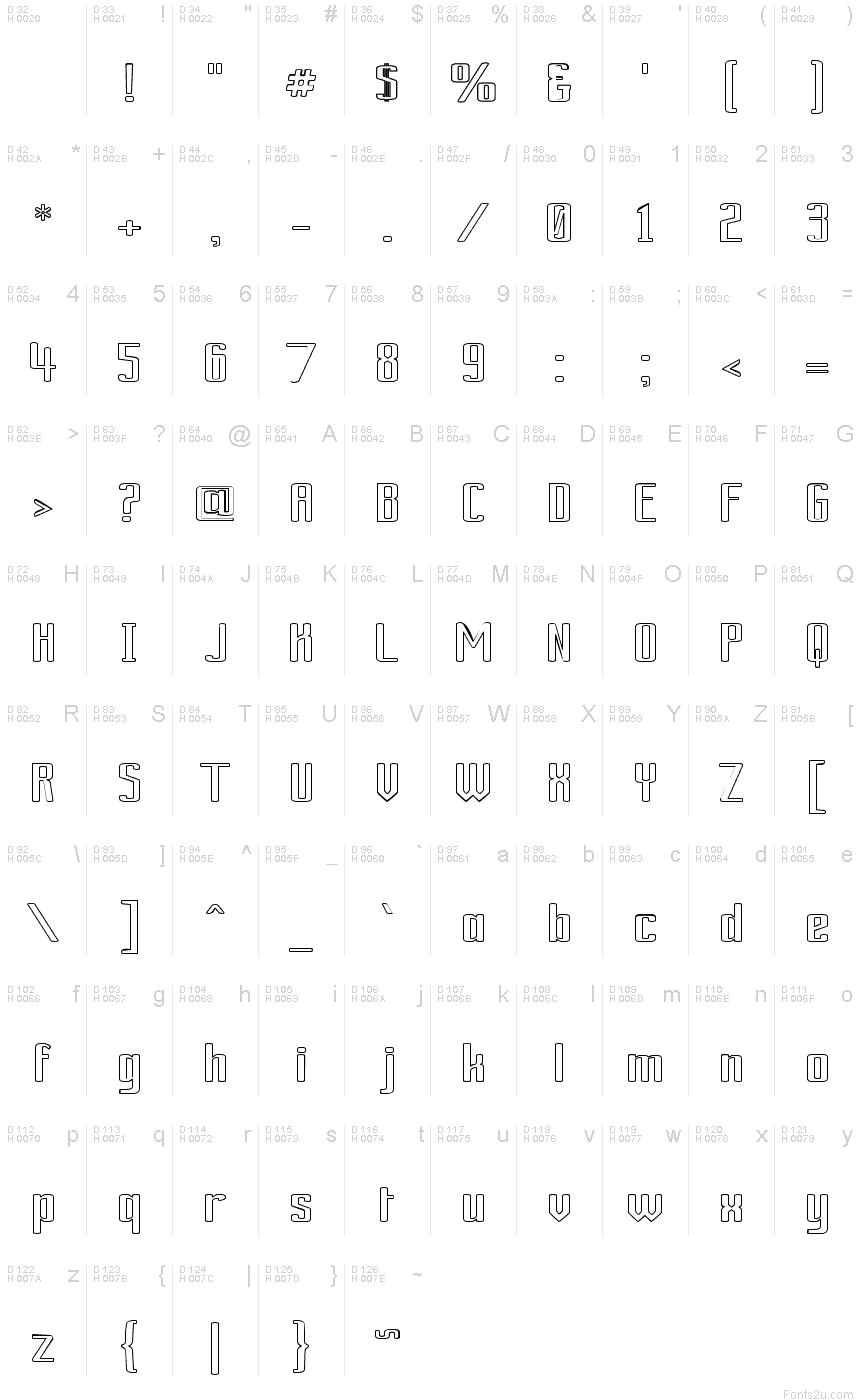
خط Ardour Outline من تصميم Graham Meade هو خط عرض مجاني مفرغ يتميز بطاقة ناعمة وأنبوبية تجعله يبدو وكأنه مرسوم يدوياً بأسلوب تزيين القوالب. تمنح مستطيلاته الدائرية وخطوطه المنتظمة الحروف مظهراً حيوياً ومنتفخاً، بينما تحافظ هندسته النظيفة على حدته وسهولة قراءته. تدعو المساحات المفتوحة داخل الحروف إلى دمج الألوان أو الأنسجة أو الصور، مما يحول كل كلمة إلى إطار يمكنك التصميم بداخله.
مع خط Ardour Outline، تكتسب العناوين والشعارات فوراً لمسة مرحة ذات طابع مستقبلي كلاسيكي (ريترو)، مع الحفاظ على مظهر نظيف ومعاصر. يتألق هذا الخط المجاني في الملصقات، وأغلفة الألبومات، وعناوين الألعاب، وعلامات الأطفال التجارية، والتغليف، ورسومات التواصل الاجتماعي الجريئة التي تبحث عن التأثير دون ثقل. جرب دمج Ardour Outline مع خط sans serif هندسي بسيط عند الأحجام الصغيرة لتثبيت التصميم والسماح لخطوطه الانسيابية بأن تكون محط الأنظار.